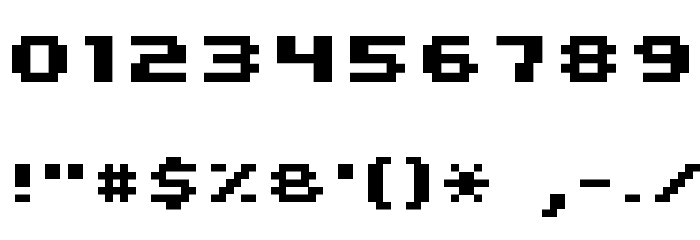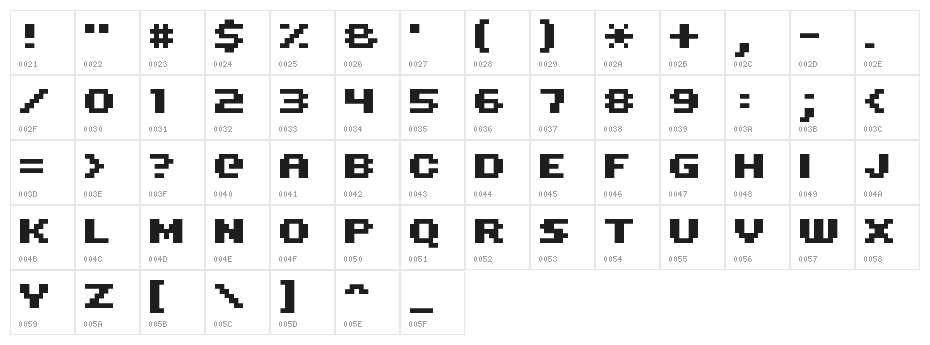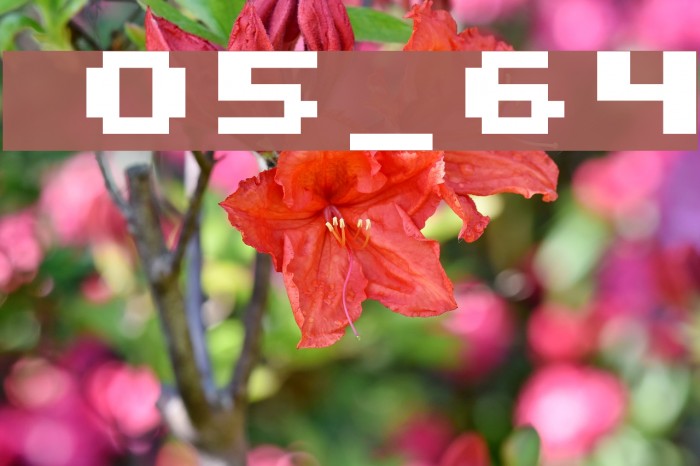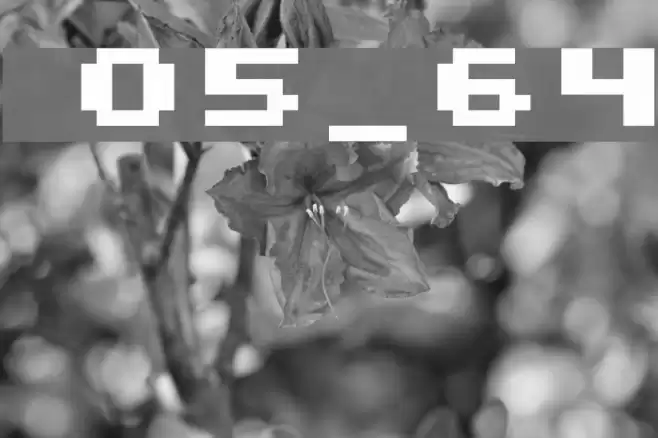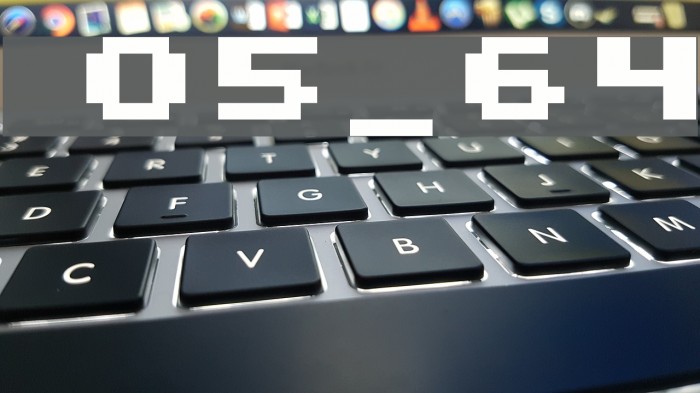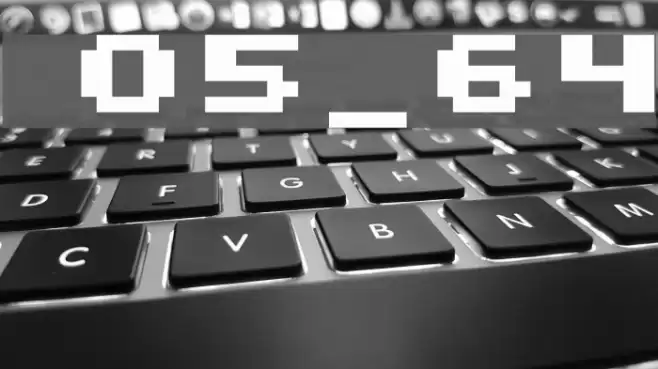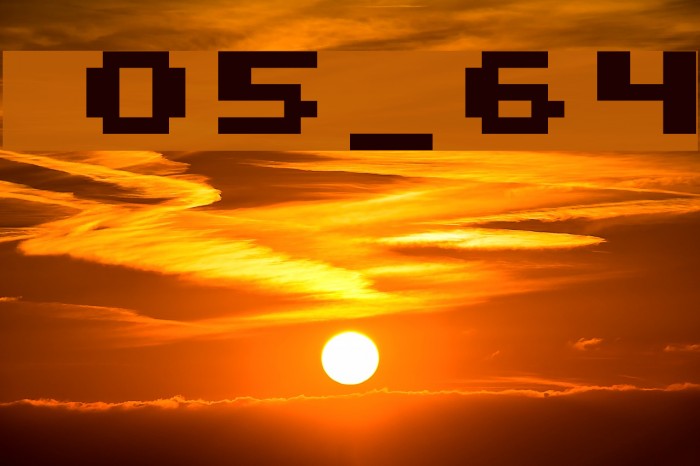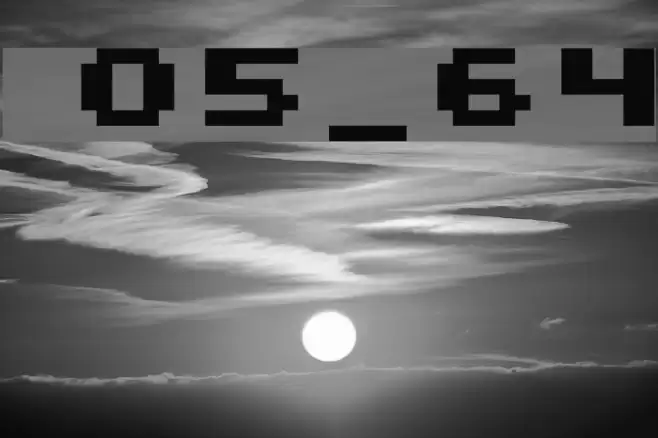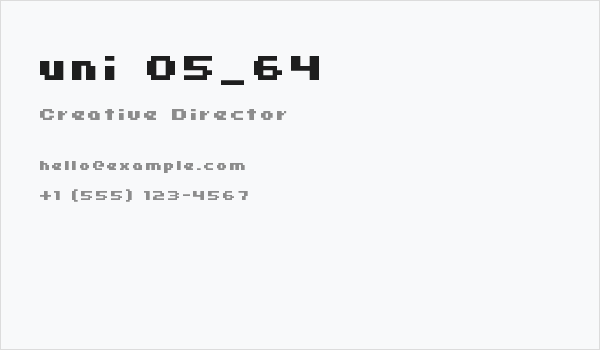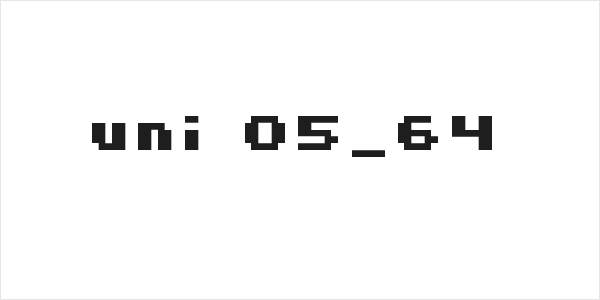
uni 05_64 Font
✎ Pixel
| Catégories | Pixel |
| Style général | Retro |
| Cas d'utilisation | Logos, Digital displays, Posters |
| Projets proposés | Ideal for video game design, retro-themed posters, digital art, and any project seeking a nostalgic or tech-inspired look. |